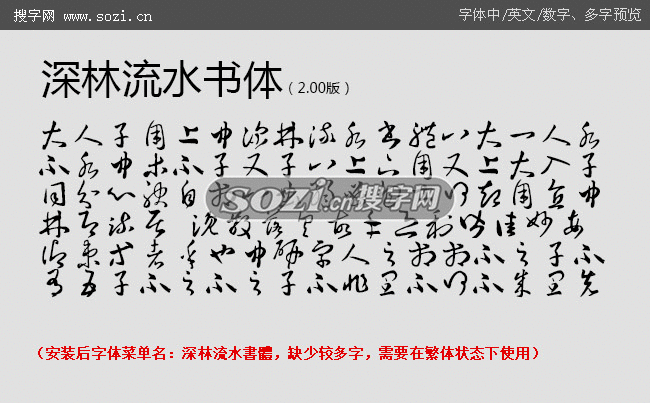
王羲之草書(shū)-深林流水書(shū)體
搜字網(wǎng)提供一款王羲之草書(shū)-深林流水書(shū)體中文書(shū)法字體下載,王羲之草書(shū)是一款非常漂亮的書(shū)法風(fēng)格字體,該字體筆畫(huà)起伏變化,富有節(jié)奏感,圓轉(zhuǎn)之中包含著提按,字勢(shì)顯得遒勁流暢。適合報(bào)紙刊頭、畫(huà)冊(cè)設(shè)計(jì)、海報(bào)設(shè)計(jì)等廣告設(shè)計(jì)應(yīng)用。
- 風(fēng)格類(lèi)別: 草書(shū)